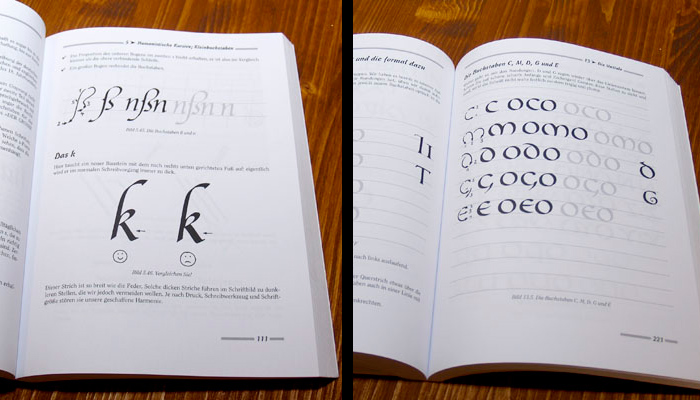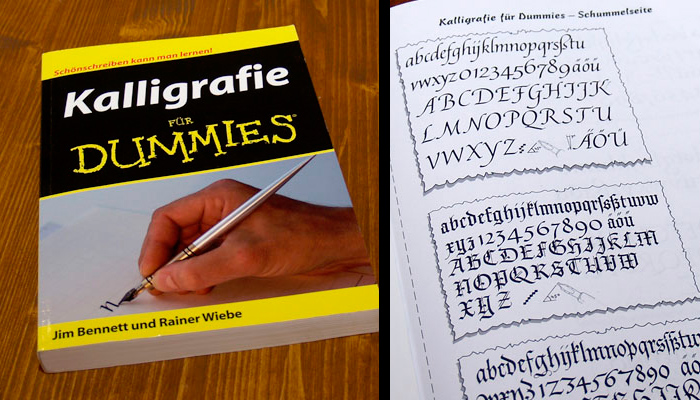
»Mit Schönschrift können Sie glänzen: Nicht nur bei Einladungen, Grußkarten oder Urkunden, Sie können auch mit Etiketten oder Aufschriften viele Alltags- und Gebrauchsgegenstände verschönern. Mit Jim Bennett können Sie die Kunst der Kalligrafie von der Pike auf lernen. Er erklärt Ihnen, welche Federn, welche Tinte und welches Papier Sie benötigen und zeigt Ihnen die grundlegenden Techniken, eine Feder richtig zu führen. Außerdem erklärt er Ihnen anhand vieler Beispiele zum Nachschreiben, wie Sie die gängigen Alphabete der Kalligrafie wie Unzial- und Frakturschriften auf das Papier zaubern.« (Klappentext)
In 20 Kapiteln geben die Autoren Praxistipps zu allem, was zur Kalligrafie dazu gehört. Angefangen bei Material und Werkzeugen, Einführungen zu zehn verschiedenen Schriften bis zum Ausrichten einer Ausstellung oder dem Umgang mit ersten Aufträgen. In einer lockeren Sprache wird dem Laien ein leichter Einstieg in die Kalligrafie geboten.
Die vorgestellten Schriften:
- Humanistische Kursive
- Textur
- Fraktur
- Römische Kapitalis
- Rustika
- Karolingische Minuskel
- Unziale
- Deutsche Schreibschrift
- Englische Schreibschrift
- Sencha-Schrift, eine fantastische Schrift
Außerdem Kopiervorlagen mit Linien und grauen Zeichen zum Nachspuren.
Auch wenn der Titel und die Gestaltung des Inhalts sich sehr von anderen Büchern zu diesem Thema sehr unterscheidet und irritiert, sind die Schriftbeispiele und Beschreibungen nicht nur einfach gehalten sondern auch sehr gut gemacht. Es ist sicherlich nicht das klassische Vorzeigebuch, das man dekorativ auf dem Schreibtisch liegen lässt, oder das einen Extraplatz im Regal bekommt. Dennoch ist es für Einsteiger auf Grund der vielen sehr praktischen Tipps und Anleitungen zu empfehlen. Der geübtere Kalligraf wird hier aber keine besonderen oder neuen Inspirationen finden.